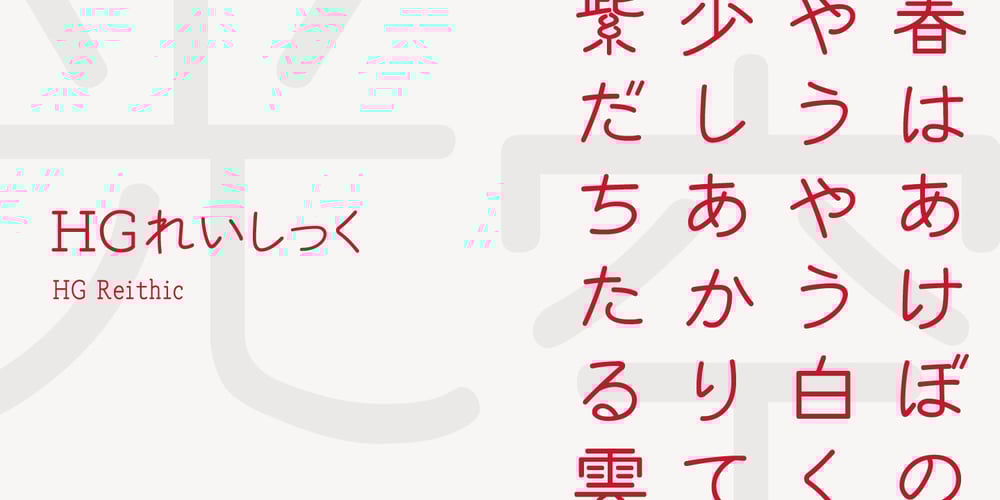
HG Reithic Font Family was designed by published by RICOH. HG Reithic contains 1 styles and family package options. シーアンドジイの「れいしっく」を字母とする書体です。隷書スタイルに影響を受けたクラシックな丸ゴシックというべき書体です。ふところが大きくとられていて判別しやすいですが、隷書の特徴をとりいれているため、カジュアルさはそれほどなく、格式と落ち着きが感じられます。そのため、フォーマルな場面に向くでしょう。隷書の特徴のある漢字はとても目を引くため、大きいサイズで使うのも、個性が発揮できます。